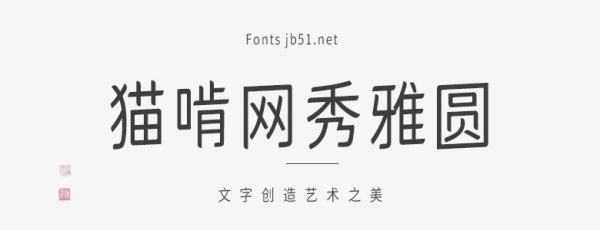
貓啃網(wǎng)秀雅圓是@新愚公基于MAX的獅尾半月字體進(jìn)行了壓縮及傾斜處理的一款字體,使字體看上去更秀雅。適合于文化類(lèi)的宣傳設(shè)計(jì)、商業(yè)類(lèi)品牌的廣告和產(chǎn)品包裝設(shè)計(jì)以及個(gè)性化文字排版等較多場(chǎng)景 .